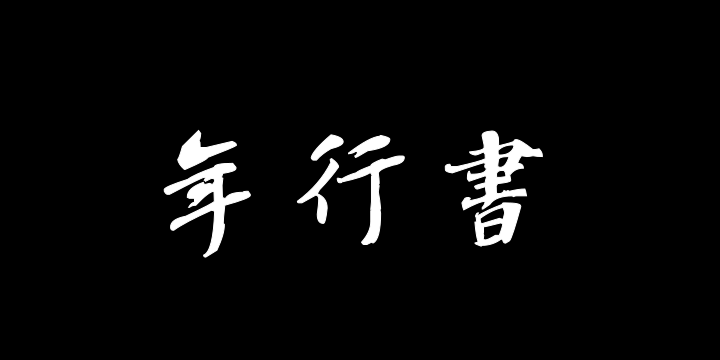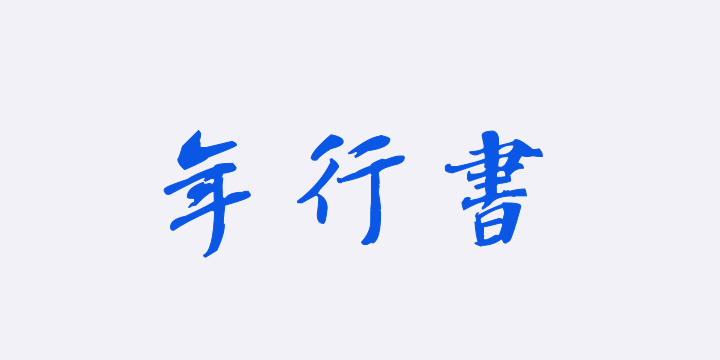
字体全名: 汉标彭年行书诗翰册
字体简介: 下载须知:本字库非标准GB2312字库。本字库只包含了彭年《诗翰册》真迹上的“735个字”。此册书法欹峭微侧,有苏轼书法意韵。王世贞《吴中往哲像赞》云:彭年 “书初法晋人,己为楷,其小者信本(欧阳询),大者清臣(颜真卿),行、草则子瞻(苏轼)。”但彭年舍苏轼丰腴、偏肥、卧笔,而以清劲爽健的笔锋使其笔法更为开放活泼,故王世贞又云:“行、草眉山若远耳。”